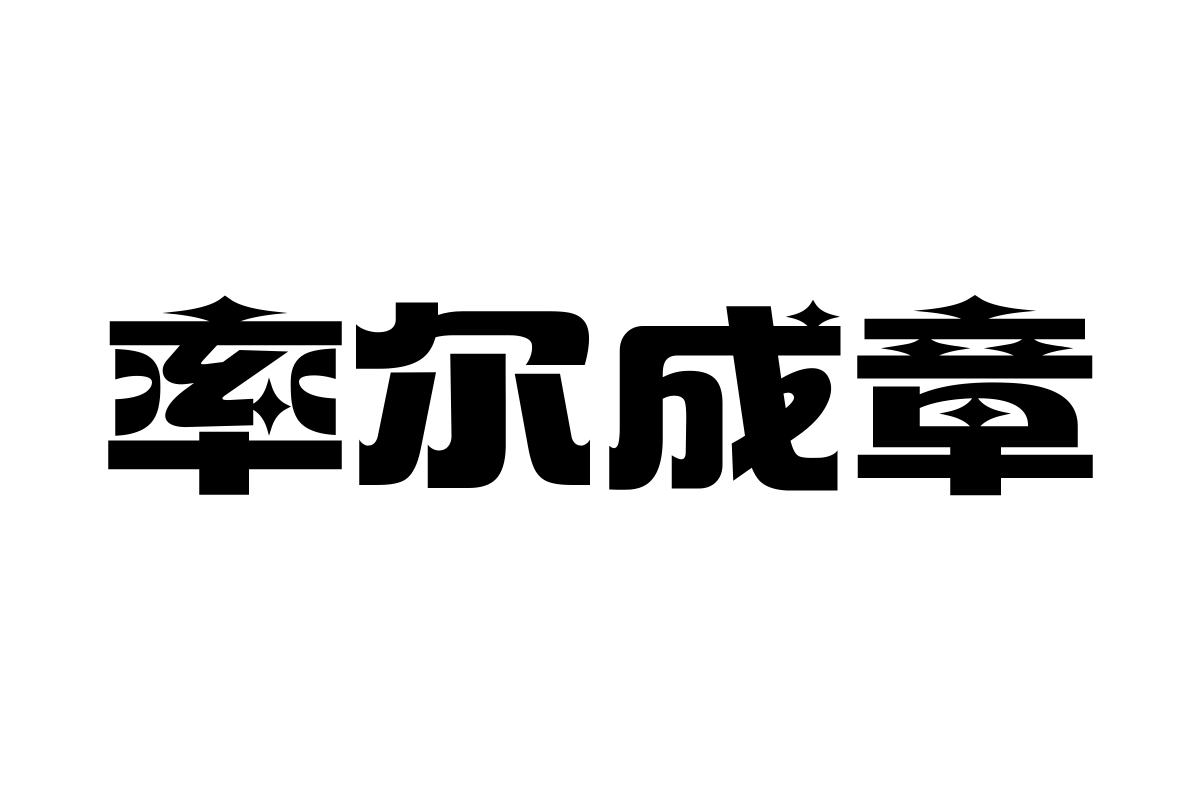
汉仪永字动感光波是一款现代感十足的中文字体,它以其独特的动感和光泽效果而著称。这款字体的设计灵感来源于传统的永字,但又融入了现代设计元素,使其在视觉上更加引人注目。
永字动感光波的笔画流畅,线条粗细适中,既保留了传统汉字的书写美感,又增添了现代设计的动感和活力。它的每一个笔画都仿佛在跳动,给人一种生动活泼的感觉。
此外,永字动感光波还具有很好的可读性,无论是在印刷还是电子屏幕上都能清晰显示,不会造成视觉疲劳。同时,它的应用场景也非常广泛,不仅可以用于书籍、杂志等传统媒体,还可以应用于广告、海报、网页等现代媒体,为各种设计需求提供丰富的选择。
总的来说,汉仪永字动感光波是一款兼具传统与现代、易读性与美观性的优秀中文字体,值得设计师们尝试使用。